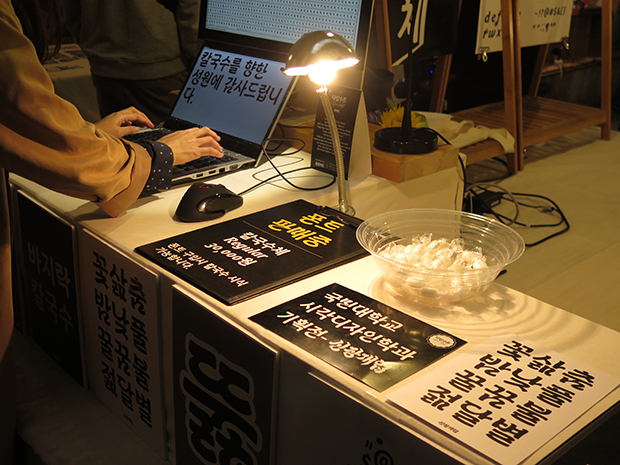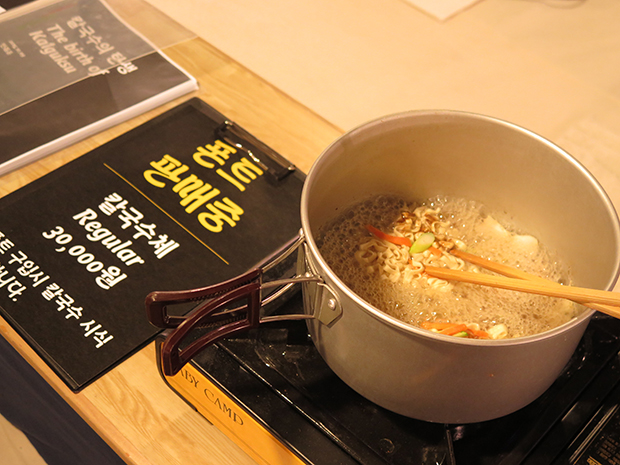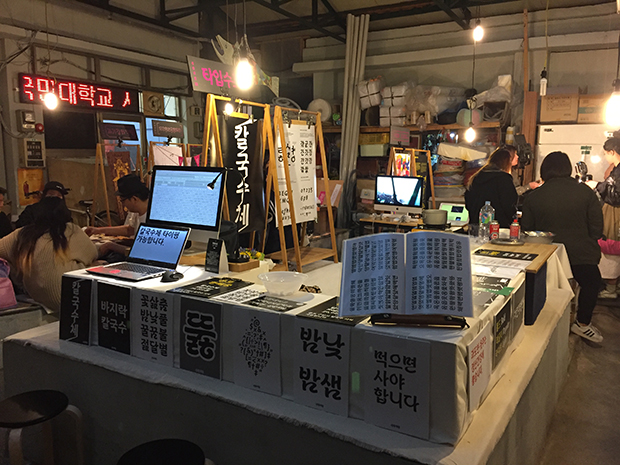
타입수프 : 칼국수체 한그릇 드셔보세요
칼국수라는 이름은 글자 형태에서 따온 이름입니다. 서체 파일 내부에는 한글 2,350자, 기초 문장부호와 기호, 로만 알파벳 50여 자가 들어 있습니다. 형태적으로 휴머니스트 산세리프에 가깝다고 할 수 있고, 받침이 있는 글자인 경우 부분적으로 중성과 종성이 붙어서 흘려 쓴 듯한 효과를 내도록 디자인했습니다.
저는 언제나 글자를 설계하고 글자꼴로 말하는 작업에 흥미가 있었습니다. 때문에 대학 생활을 결산하는 작품은 서체가 아니면 안 된다고 생각했습니다. 또한, 다양한 디자인 졸업작품들이 매년 나오지만 근본인 서체 작업물은 중요성과 비례하면 매우 적은 편입니다. 그래서 KS코드를 충족시킬 수 있는 전체 글자가 담긴 서체 작업을 시도했습니다.
졸업전시 기간 내 연남동 동진시장 내부에 위치한 ‘타입수프’ 코너에서는 서체 칼국수체를 타이핑하고 엽서와 견본집을 관람할 수 있도록 했으며, 칼국수체 파일을 구매한 분들께는 현장에서 칼국수를 끓여 대접했습니다.
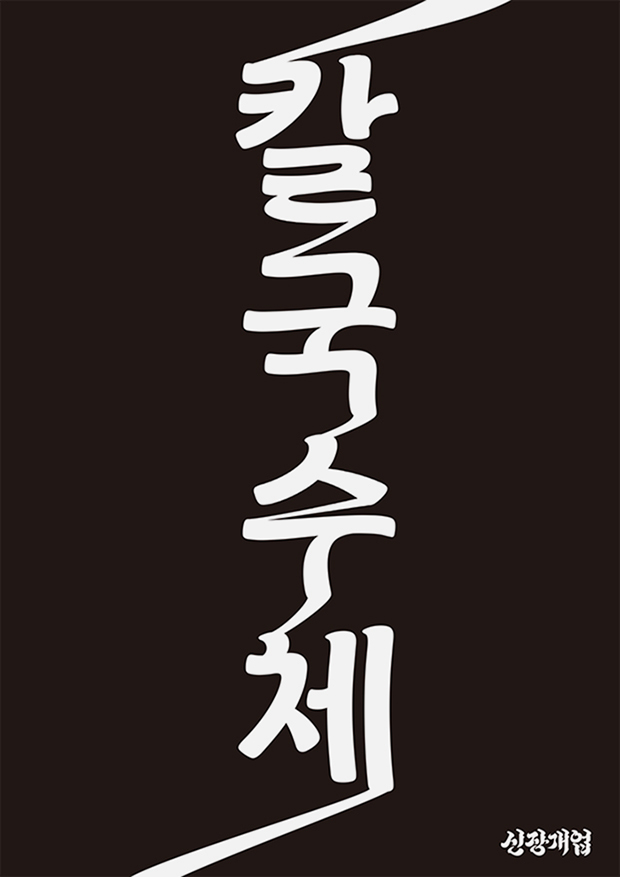
칼국수체의 특징에 대해 보다 자세히 설명한다면요. 더불어 졸업전시에서 서체 판매에 그치지 않고 칼국수를 대접하게 된 계기도 함께 듣고 싶습니다.
칼국수라는 이름은 글자 형태에서 따온 이름입니다. 서체 파일 내부에는 한글 2,350자, 기초 문장부호와 기호, 로만 알파벳 50여 자가 들어 있습니다. 형태적으로 휴머니스트 산세리프에 가깝다고 할 수 있고, 받침이 있는 글자인 경우 부분적으로 중성과 종성이 붙어서 흘려 쓴 듯한 효과를 내도록 디자인했습니다. 칼국수체는 작게 쓸 것을 노리고 만든 서체는 아닙니다. 서체 형태의 특징이 뚜렷하기 때문에, 짧은 표제에 사용될 때 ‘칼국수’가 가진 리드미컬함이 극대화되지 않나 싶습니다.
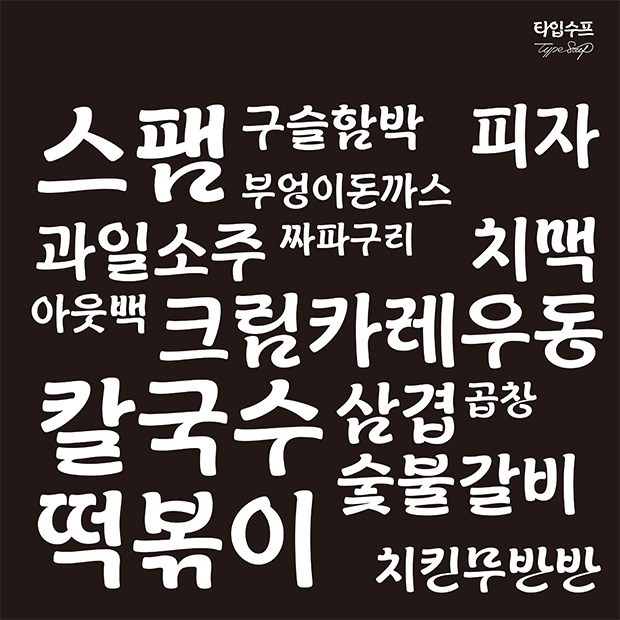
칼국수를 대접하게 된 것은 전시 전체 컨셉과 관계가 있습니다. 전시가 열렸던 동진시장은 동네에서 조그만 재래시장과 비슷한 장소입니다. 단순히 세련되고 깔끔한 전시관에서 밖으로 나가기만 한 것이 아니라 시장이라는 맥락에 녹아들어야 할 필요가 있었죠. 그래서 디자인 기초 재료인 서체와 ‘시장’하면 떠오르는 분식류인 국수를 같이 판매하기로 했습니다.
디자이너로서 서체에 관심을 갖는 것은 일정 부분 당연하지만 서체 제작에까지 흥미를 두는 것은 또 다른 차원의 문제입니다. 레터링 작업 및 서체 제작에 관심을 갖고 있는 특별한 이유가 있나요?
디자이너의 작업물은 크게 타입과 이미지 두 개로 분해할 수 있습니다. 중요도라는 관점에서 보면 이미지는 타입을 보조하는 역할이라고 생각합니다. 결국 타입이 핵심인 셈입니다. 그래픽 디자이너들은 기존 서체를 가지고 결과물을 제작하지만 저는 좀 더 기초적이고 핵심적인 요소에 접근하고 싶었습니다. 출생의 비밀을 푸는 기분이었다고 하면 비슷한 묘사가 되겠네요.
이건 살짝 다른 얘긴데, 과거와 비교해서 점점 더 단발성 레터링이 아니라 ‘서체’를 다루는 졸업작품들이 늘어나고 있습니다. 점점 더 늘어날 것이고 이번 해가 일종의 시작점이 아닌가 합니다. 기술 발전 그리고 동시에 교육의 혜택을 입은 세대가 이제 대학 밖으로 나갈 때가 된 거죠. 그래픽 디자이너를 꿈꾸는 대부분의 학생들이 서체 작업 그 자체를 원하지는 않습니다. 하지만 둘의 관계를 생각할 때 근본에 접근할 수 있다는 건 분명 강점이 될 것입니다.
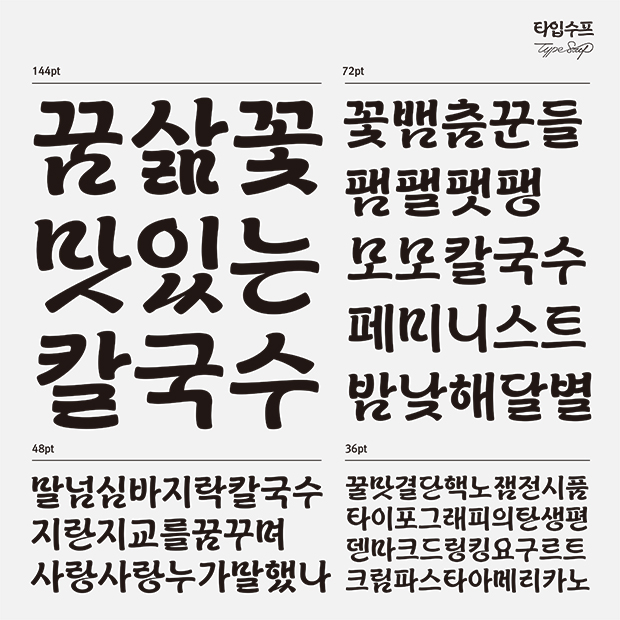
졸업전시가 상호 교류를 기반으로 하는 만남의 장 형식을 갖고 있었죠. 관람객들로부터 들은 반응이나 피드백이 궁금합니다.
전시자 모두 상주하는 전시 특성상 지인뿐 아니라 온라인상에서 교류하던 좋은 사람들을 실제로 많이 만났다는 것이 큰 수확이었습니다. 또한, 디자인과 졸업전시는 그 특성상 해당 분야 종사자나 학생들 위주로 관람객이 편중되는 편인데 이번에는 일반인분들이 많이 오셔서 다양한 코멘트를 남겼습니다.
그중 서체를 어떻게 판다는 것인지, 설치는 어떻게 하는지 등 기초적인 것을 물어보았던 질문이 기억에 남습니다. 그런 분들께 설명함으로써 디자이너와 일반인 사이의 간극을 좁힐 수 있어서 기뻤습니다. 더불어 시각물 생산자와 구매자가 시장에서 직접 만난 순간을 기념하기 위해 칼국수체 구매자의 이름을 쓴 글리프를 서체 안에 넣었는데요, 일러스트레이터의 글리프 패널에서 볼 수 있습니다.
전시 모습
‘칼국수체’를 앞으로 어떻게 활용하고자 하는지 추가 계획이 있다면 듣고 싶습니다. 또한 앞으로의 목표도 궁금합니다.
서체 제작은 단발성 프로젝트가 아닙니다. 만들어 선보인 때부터가 시작이고, 계속 다듬으며 발전해 나가는 것이 이상적인 형태입니다. 기존 구매자로부터 단점 및 오류 리포트를 받아서 수정/보완하고 패밀리를 더욱 세부적으로 나눈 ‘칼국수2(가제)’를 준비 중입니다.
구상하고 있는 진로는 타입 디자인 회사에 들어가서 타입을 근본까지 파헤치는 것, 그리고 시각디자인 내 다른 영역 구성원과도 교류하며 작업을 지속하고 싶습니다. 우리나라 서체 디자이너의 활동 반경은 상당히 좁은 게 사실인데, 시각 기초 재료 생산자와 사용자가 분리되면 안 된다고 보기 때문에 앞으로도 꾸준한 교류를 지향합니다. 궁극적으로는 타입 디자인과 레터링에 강점을 둔 스튜디오를 설립하는 게 목표입니다